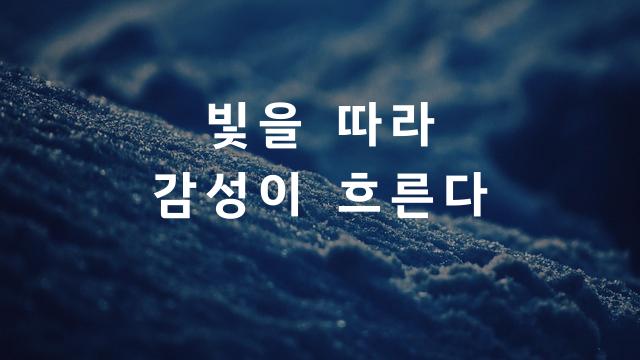
모노플렉스Nerd Italic은 기본 고딕 스타일을 기반으로 한 문서용 이탤릭 폰트로, 세련되면서도 읽기 쉬운 구조를 갖추고 있습니다. 디자인과 기능성을 겸비하여 다양한 문서 작성에 최적화되어 있습니다.
모노플렉스Nerd Italic은(는)
기본 고딕, 감성적인, 부드러움 계열의 생김새를 가지고 있으며
웹/앱 디자인, 보고서/문서 등에서 자주 활용되며, 효과적인 메시지 전달에 적합합니다.
이 폰트는 크리에이티브, 기술/IT 분야에 잘 어울리며,
창의적인, 전문적인 느낌을 담고 있는 것이 특징입니다.